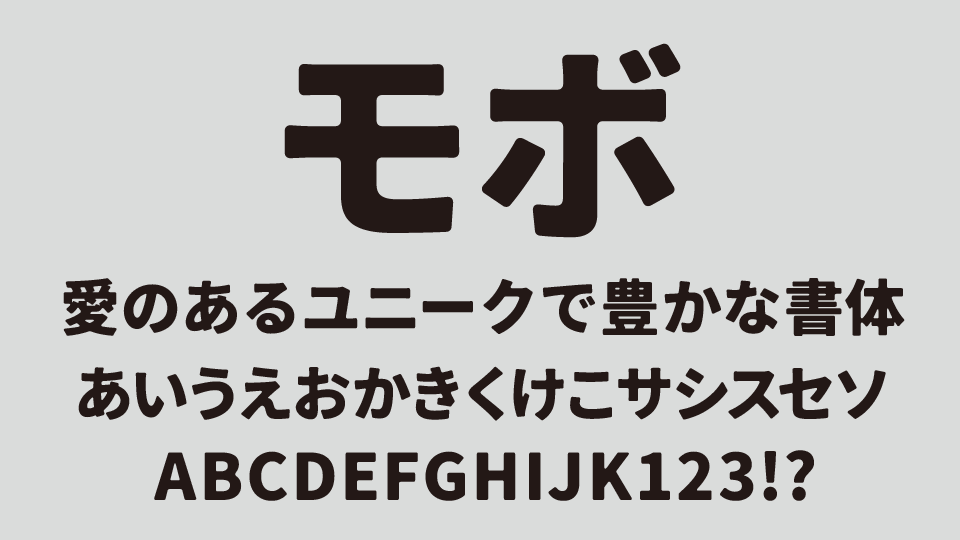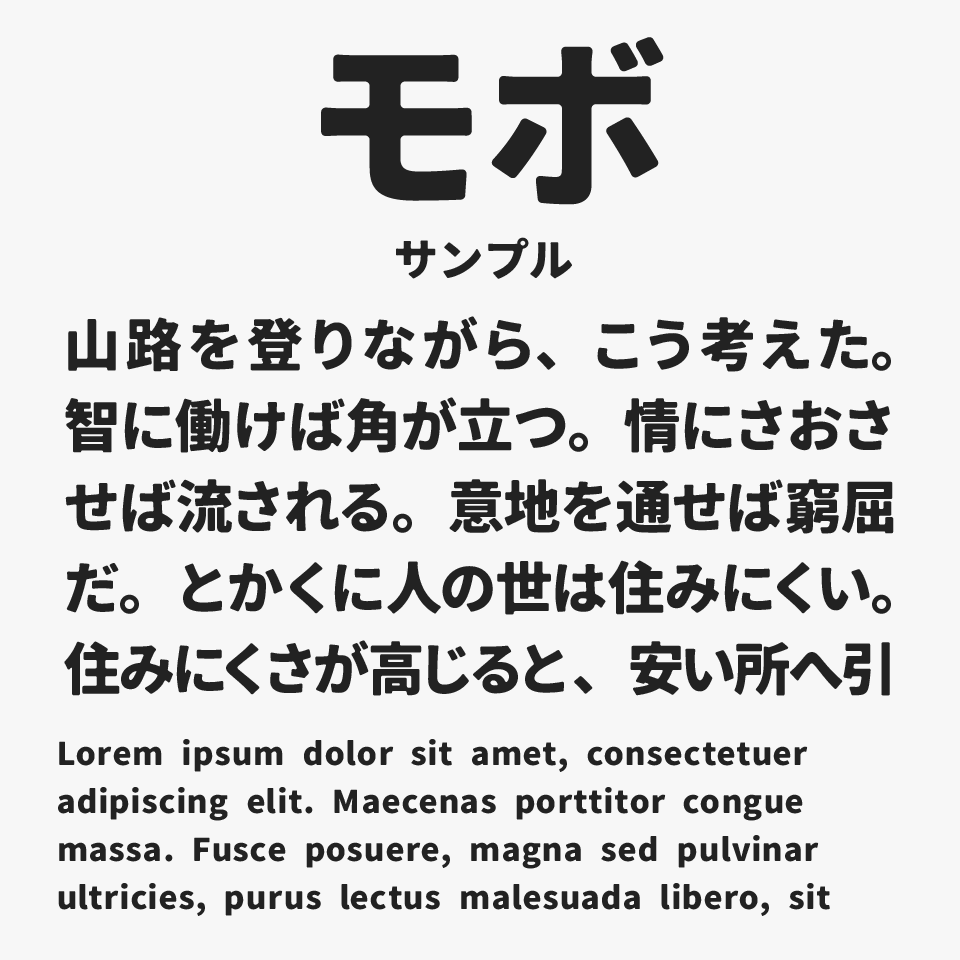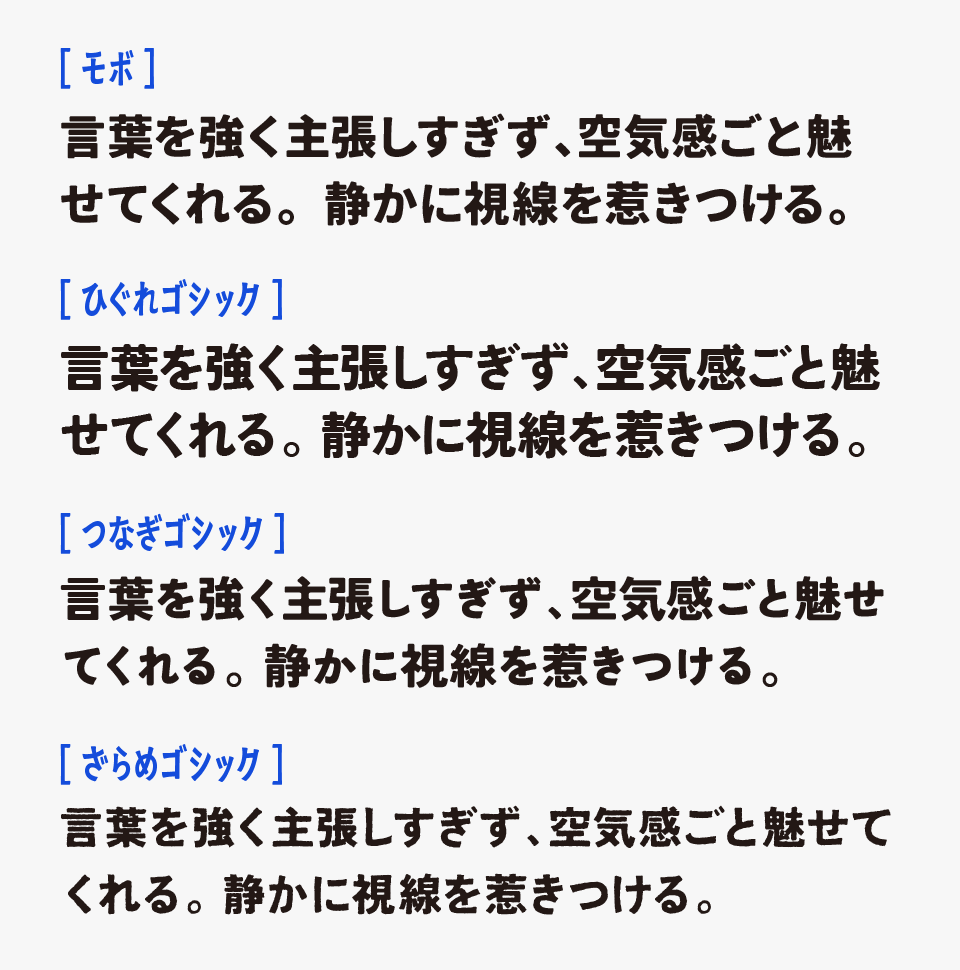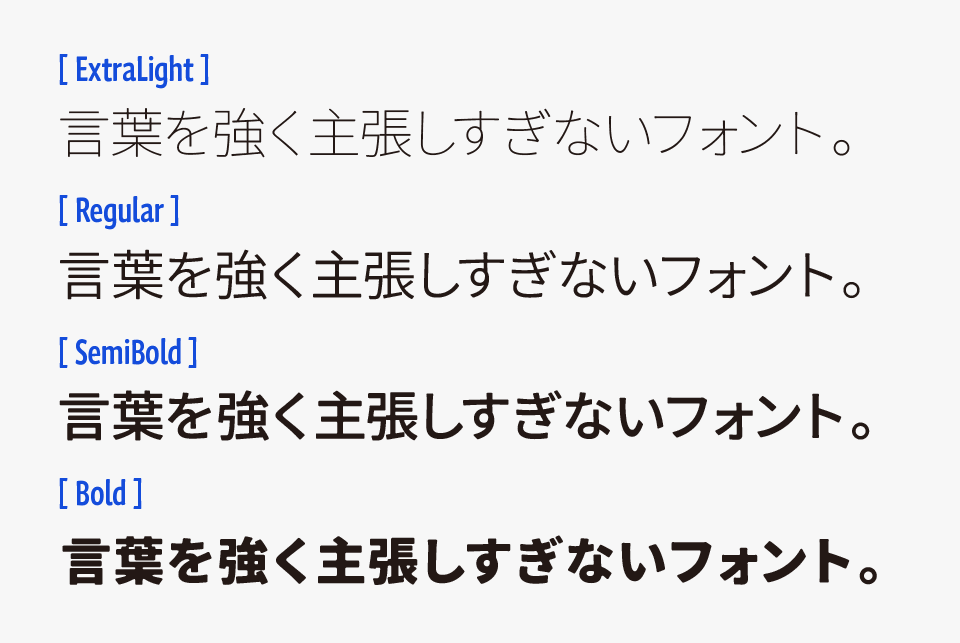
モボ
モボフォントは、「源ノ角ゴシック」をベースに、モダンな骨格を持つ角ゴシックへ角丸処理を加えることで、やわらかくレトロな雰囲気に仕上げられたゴシック体フォントです。
しっかりとした太さがあるため存在感は抜群ですが、文字の角が丸く整えられていることで、力強さの中にも親しみやすさがあるフォントと仕上がっています。内側(スミ処理)も施されているので、墨がにじんだような質感も感じられます。
インパクトがありながら読みやすさも保たれているため、タイトルや見出し、ロゴ、動画サムネイルなど、目を引かせたい場面にもぴったりなフォントとなっています。
モリサワのA1ゴシック好きの方にもとってもオススメで、スミ処理の角丸処理など柔らかい雰囲気などが少し似ています。
墨がにじんだような質感を持つほかのフォントと比較すると、モボフォントは全体的にやわらかく親しみやすい印象に仕上がっています。(比較フォントは、ひぐれゴシック、つなぎゴシック、ざらめゴシックと比較しています。合わせてチェックしてみてください。)
ウェイトもBold、SemiBold、Regular、ExtraLightが揃っているので、見出しから本文テキストなどにまで使用することができそうです。
収録文字は、ひらがな・カタカナ・漢字・アルファベット・数字・記号が収録されています。